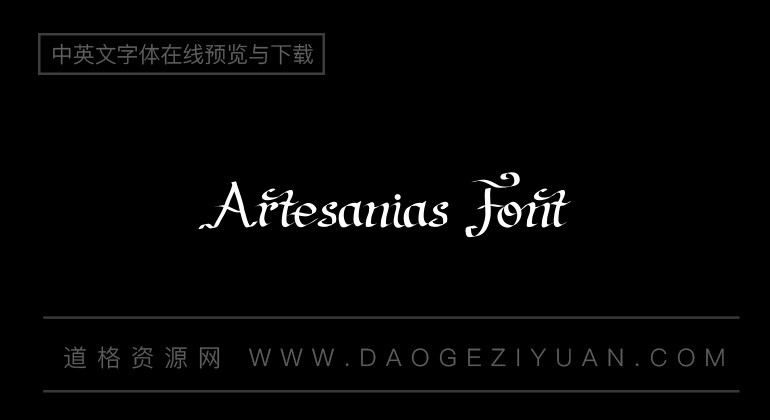
Artesanias Font 是一种美观和独特的字体,适用于各种设计项目。它是一种手写风格的字体,具有流畅的曲线和不规则的形状,使得它看起来非常有艺术感和个性。 Artesanias Font 包含大写字母、小写字母、数字和标点符号,可以满足各种文字排版需求。此外,它还包含一些特殊字符和装饰符号,可以用于添加额外的视觉效果和装饰。 Artesanias Font 的设计旨在传达一种手工制作和创造性的感觉,适用于各种设计项目,如海报、标志、包装、书籍封面、卡片和网站设计等。如果您正在搜索一种具有独特风格和艺术感的字体,Artesanias Font 是一个不错的选择。内容介绍
Artesanias Font是一款非常不错的手写艺术字体,具有很好的视觉感,适合于文化类的宣传设计、商业类品牌的广告和产品包装设计以及个性化文字排版等较多场景。